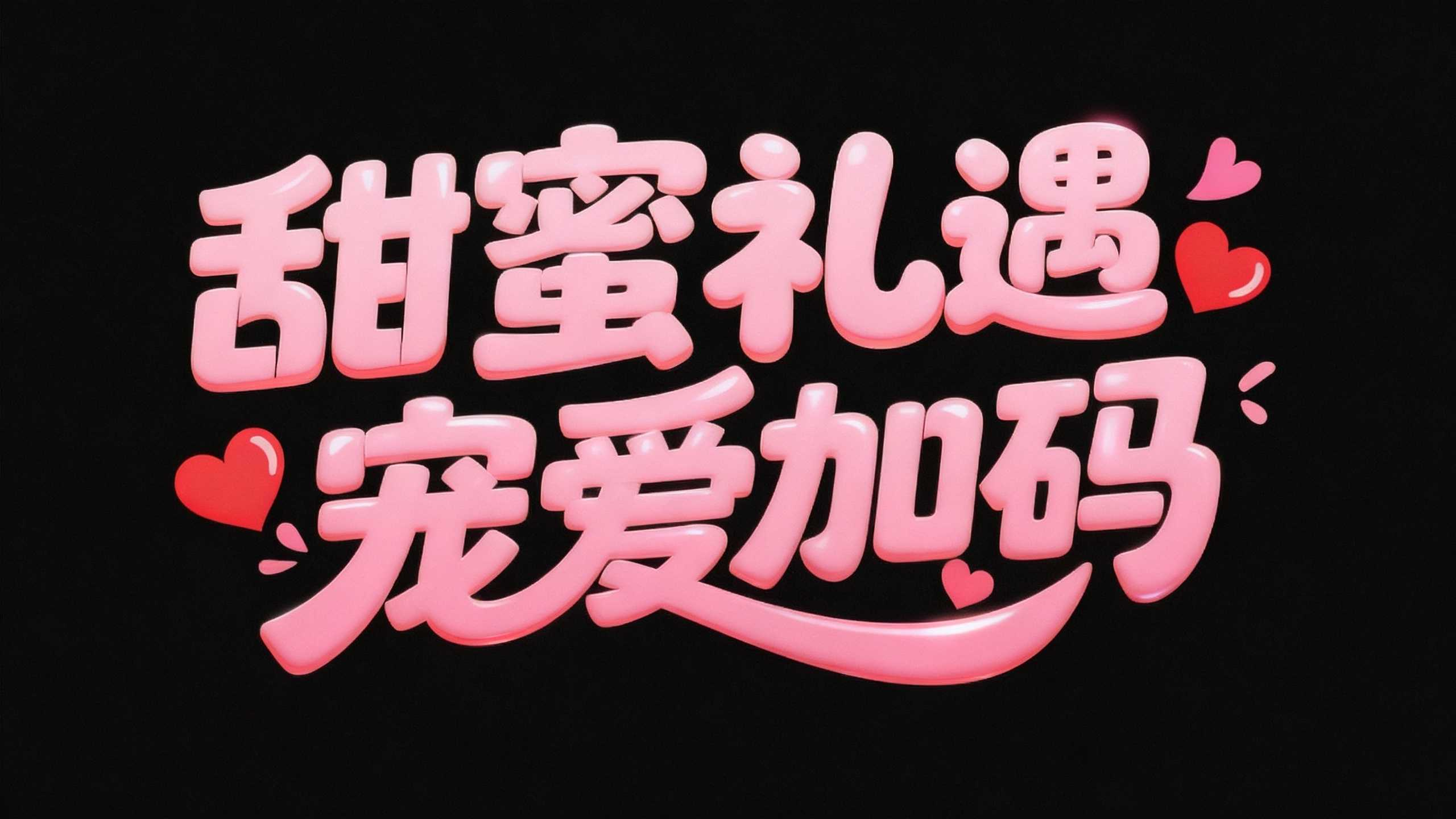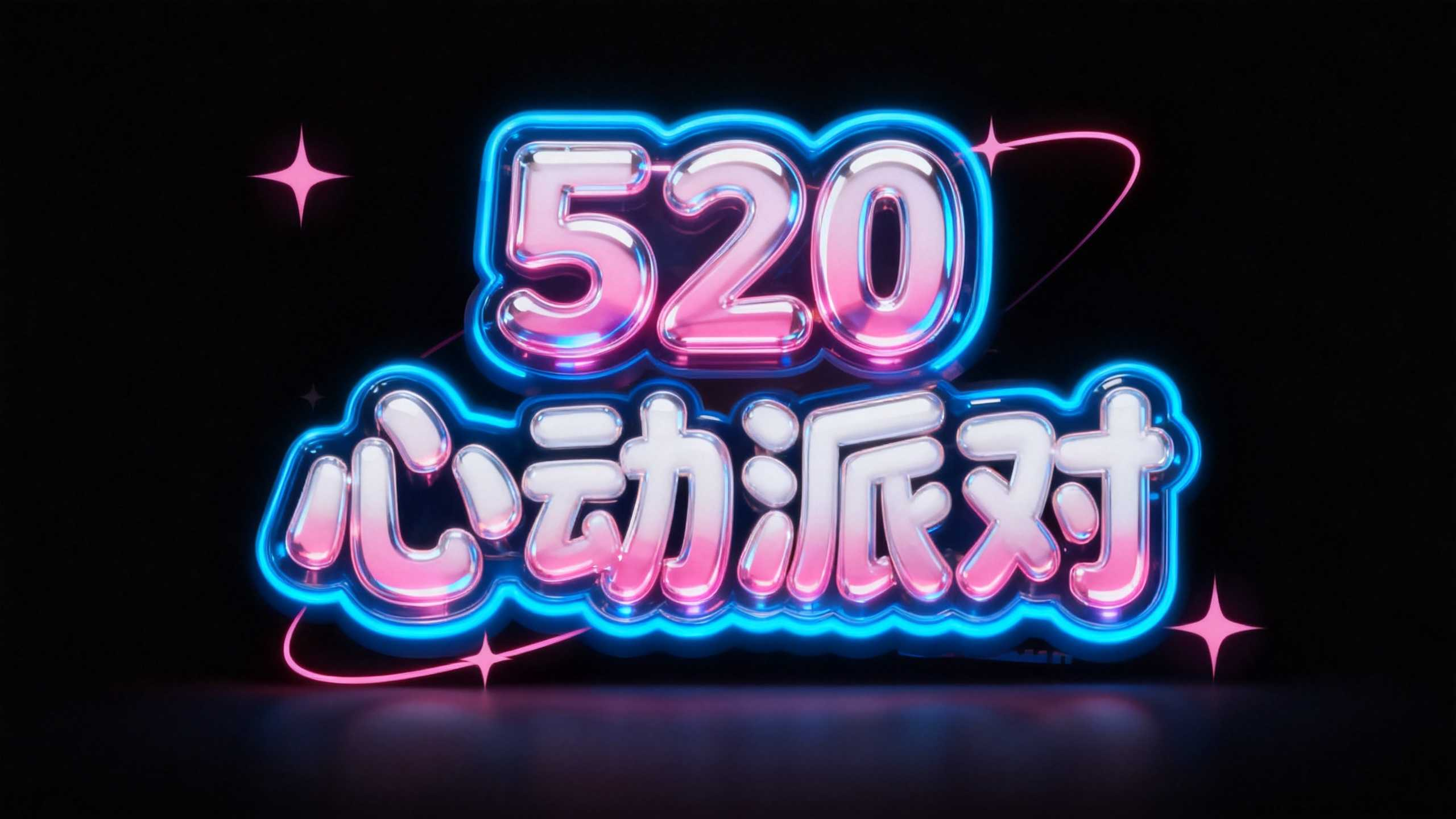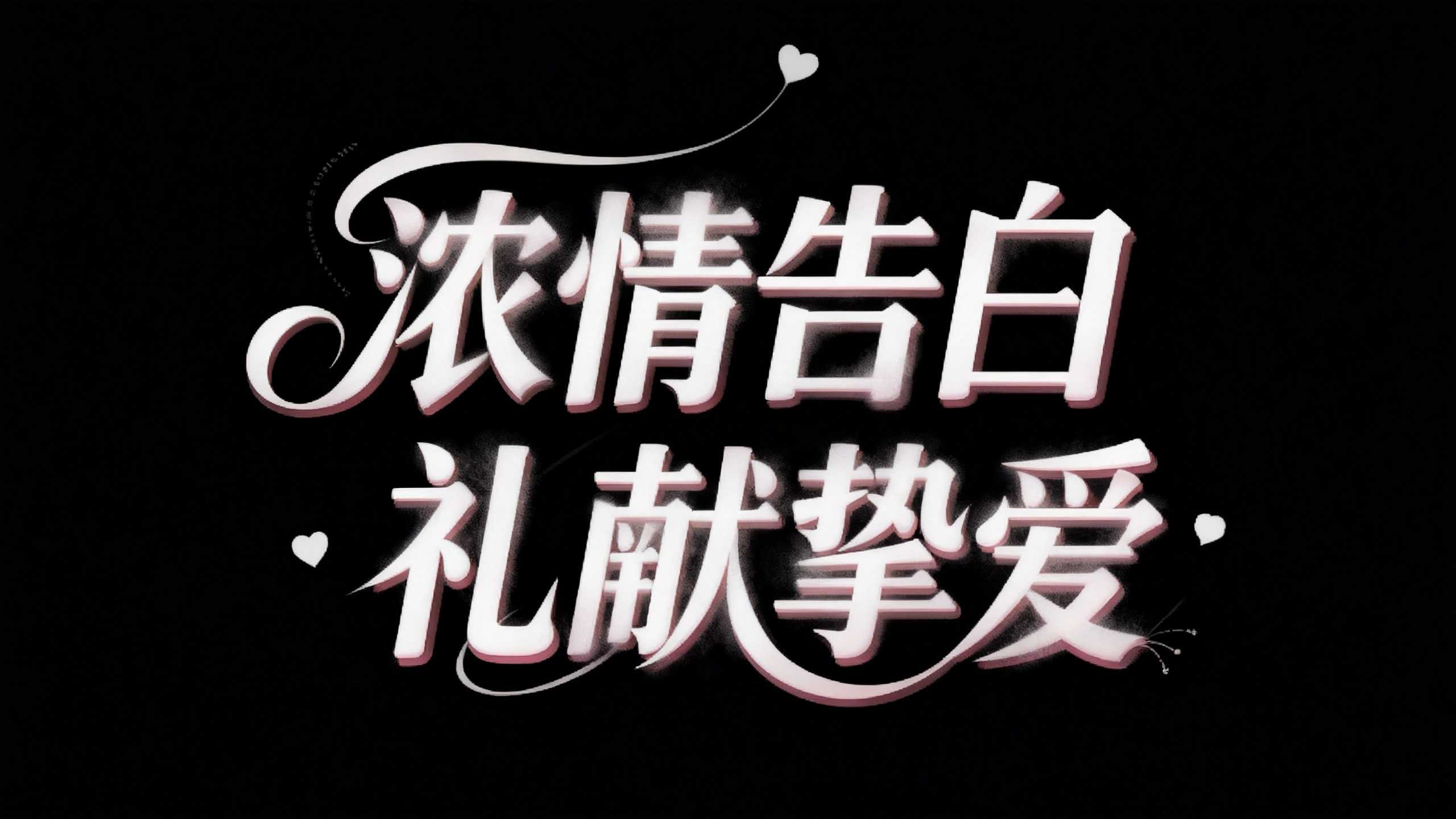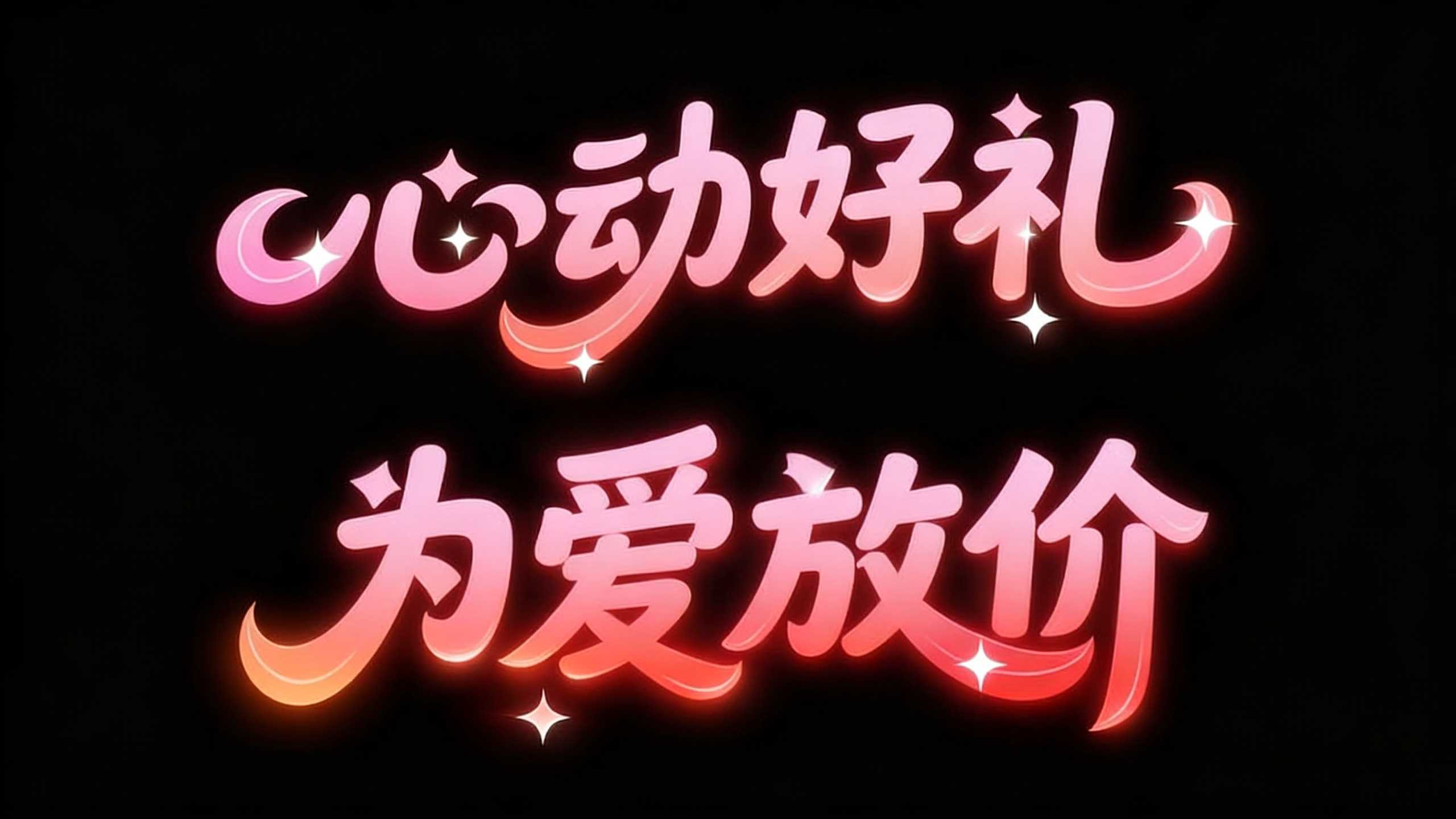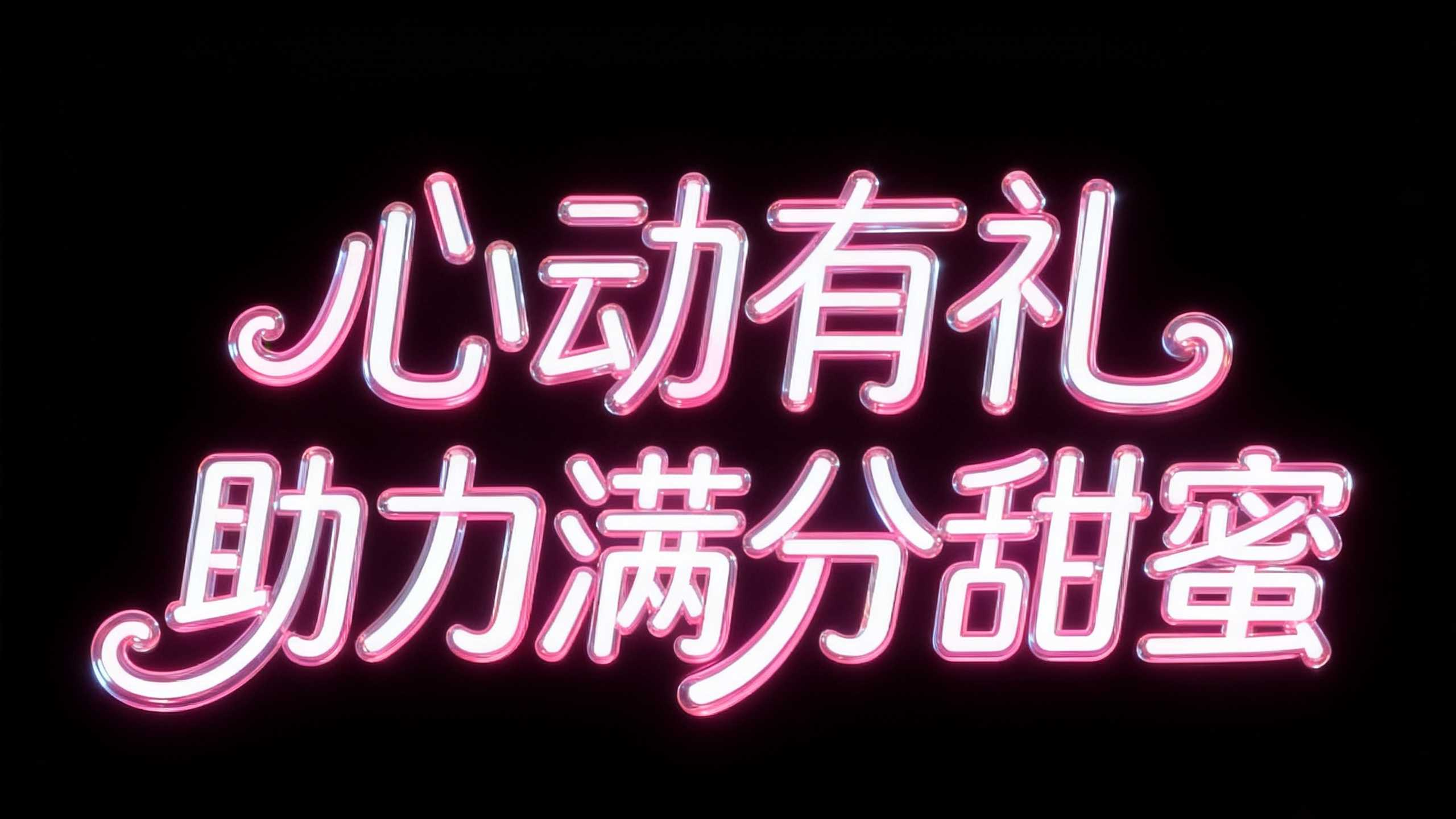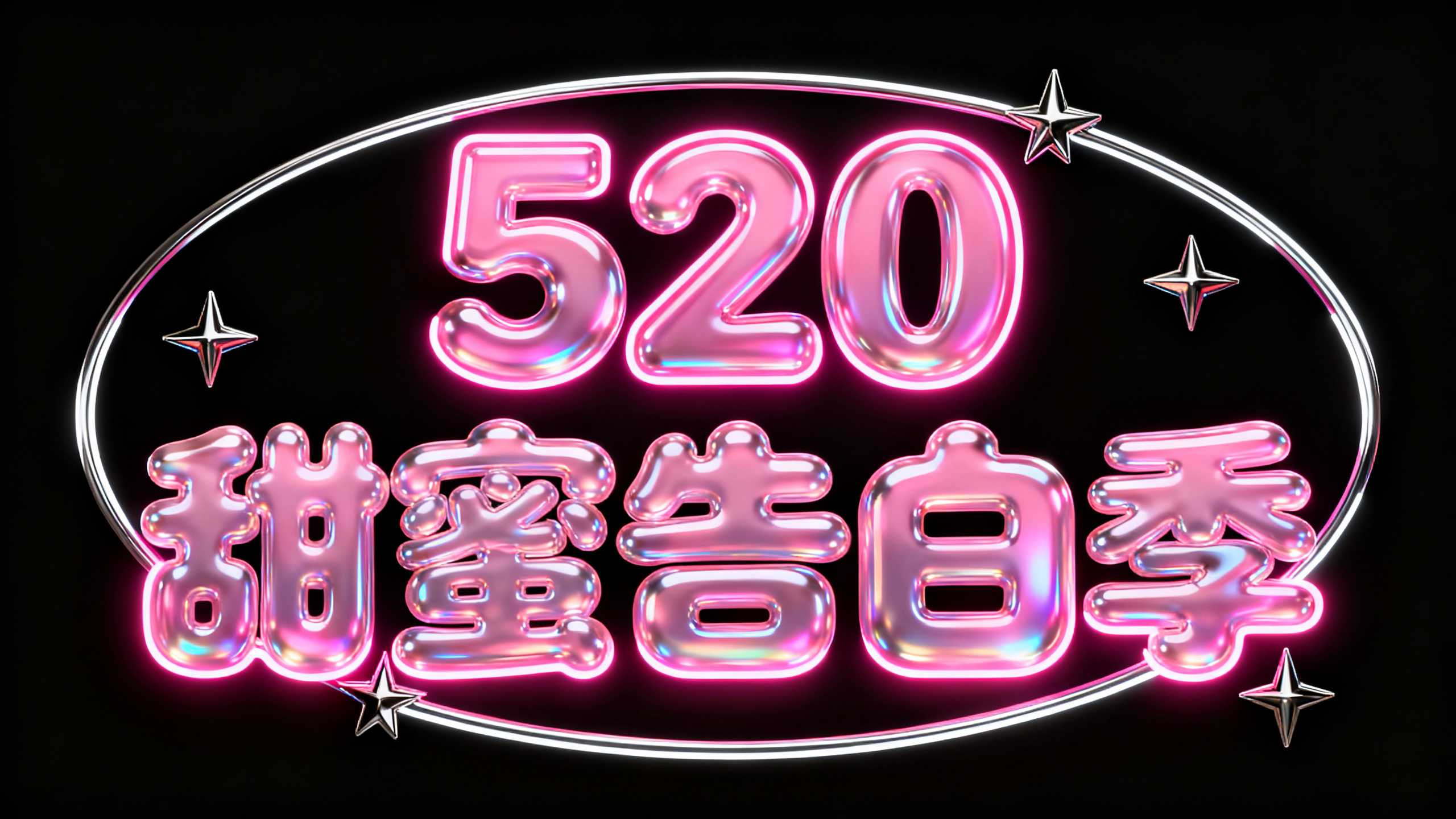
6款高甜浪漫AI字体,一键生成520情人节品牌物料!
520将至,空气中弥漫着甜蜜与浪漫的气息。无论是线上社交的官宣示爱,还是线下的情人节促销与商场活动,都需要极具氛围感的创意字体设计来助阵。以下6款专为520情人节主题定制的AI设计字体,由字由AI字体功能一键生成,让我们来看看!
「心动好礼 为爱放价」:渐变荧光特效
字体采用了粉色霓虹灯管般的渐变色彩,边缘散发着柔和的光晕,并点缀着星星元素。将甜蜜的氛围感拉满融入商业促销的属性,是兼具颜值与转化的特效字体。
核心场景应用:商场海报与线下互动:适用于商场中庭的主KV或户外大屏的大标题。直播间背景设计:美妆、珠宝类目在520大促期间的直播间背景。
「甜蜜礼遇 宠爱加码」:3D果冻质感
这款字体呈现出Q弹的3D立体果冻质感,圆润的字形配合高饱和度的马卡龙粉,辅以小巧的红心装饰,完美捕捉了恋爱中的那种软糯与幸福感,是一款极具感染力的字体样式。
核心场景应用:鲜花与甜品品牌包装:作为花束贺卡、蛋糕顶牌的海报标题字体。UI交互设计:恋爱类APP的弹窗提示、签到奖励界面。
「520 甜蜜告白季」:水晶泡泡特效
字体如同被精心吹制的透明泡泡糖或水晶,表面带有绚丽的彩虹镭射反光效果。这种高光泽度的材质显得格外耀眼,是极具视觉冲击力的创意字体设计。
核心场景应用:珠宝产品海报:作为产品海报设计的核心主视觉,映衬珠宝的璀璨光芒。H5设计与长图文设计:朋友圈刷屏的表白H5,用这款字体样式做开篇封面标题字体。
「520 心动派对」:赛博霓虹特效
结合了粉色实体字与蓝色冷光线条,营造出一种充满活力的“赛博朋克”风浪漫派对氛围。充满了动感与潮流张力,非常契合Z世代的表达方式。
核心场景应用:服饰与箱包快闪店:作为线下互动装置的大标题,打造沉浸式打卡空间。青春派对海报:音乐节、主题派对的宣传海报设计。
「心动有礼 助力满分甜蜜」:梦幻灯管特效
经典的粉色渐变,字体轻盈灵动。有着极强的柔美特质,能够轻易软化商业促销的硬朗感,传递出品牌对消费者的温柔关怀。
核心场景应用:美妆与轻奢品牌:适用于情人节礼物推荐的banner设计或主视觉。微信推文配图:品牌公众号发布的表白指南推文,用其作为海报标题字体。
「浓情告白 礼献挚爱」:典雅华丽衬线
字体设计回归经典,带有华丽的装饰性曲线。适合用来表达郑重其事的承诺与敬意。
核心场景应用:高定珠宝与奢侈品宣传:高端情人节促销物料的封面标题字体。恋爱纪念册与婚礼请柬:作为长图文设计中的章节大标题。